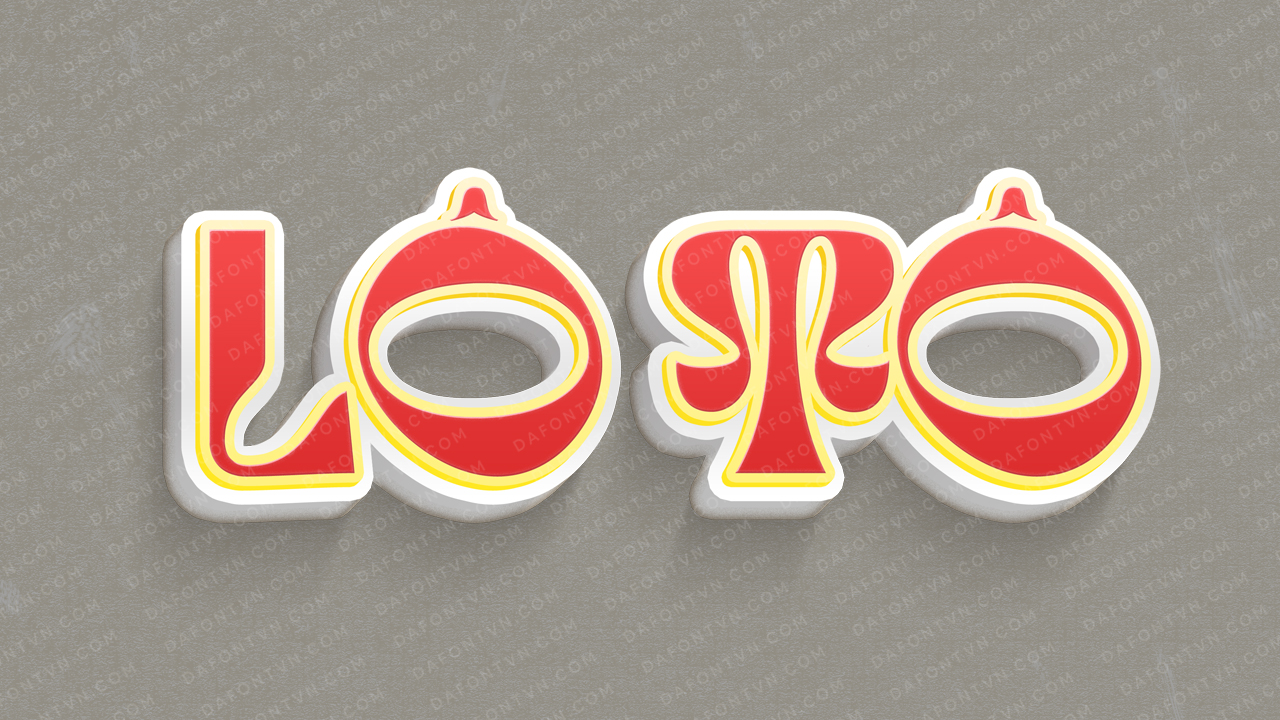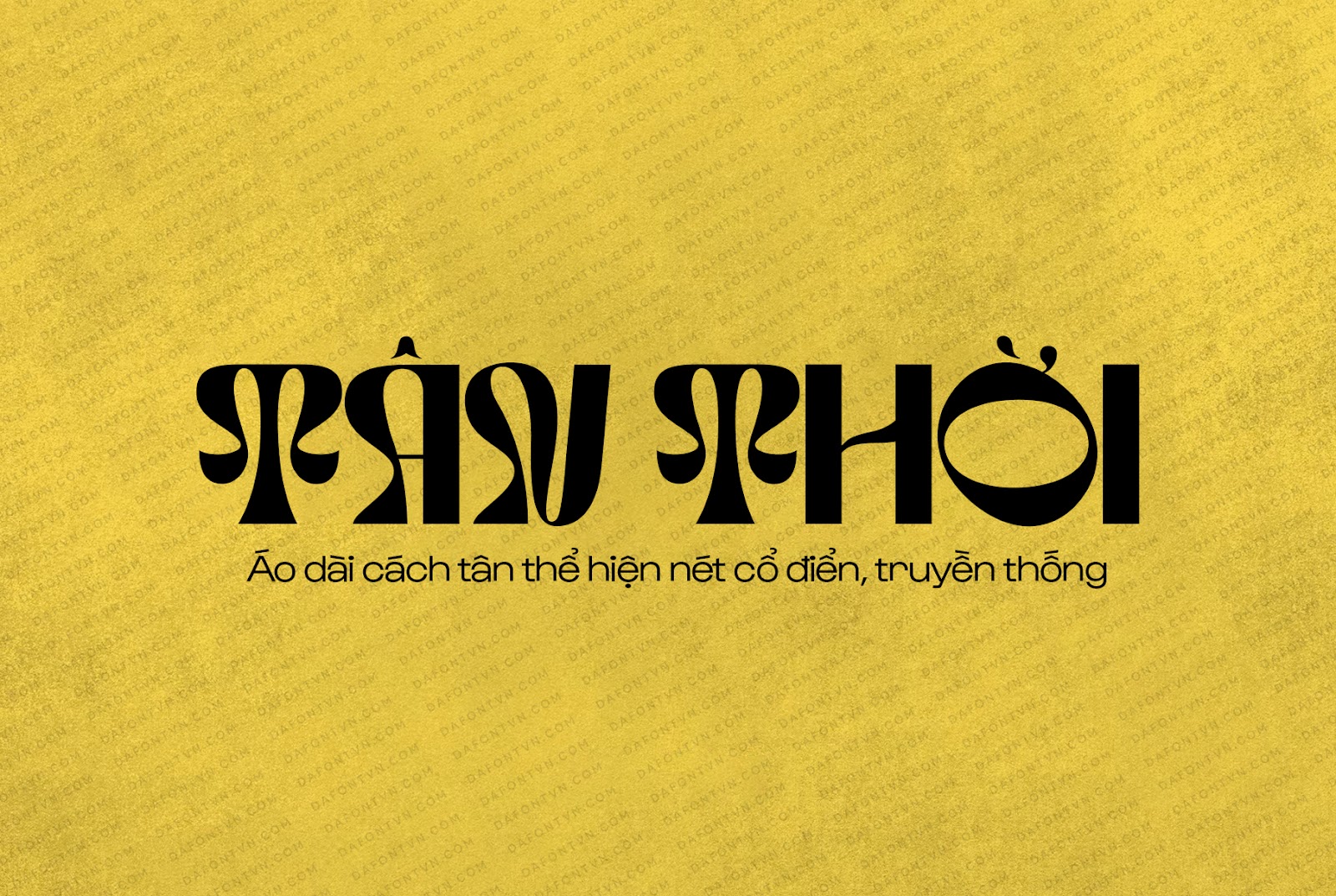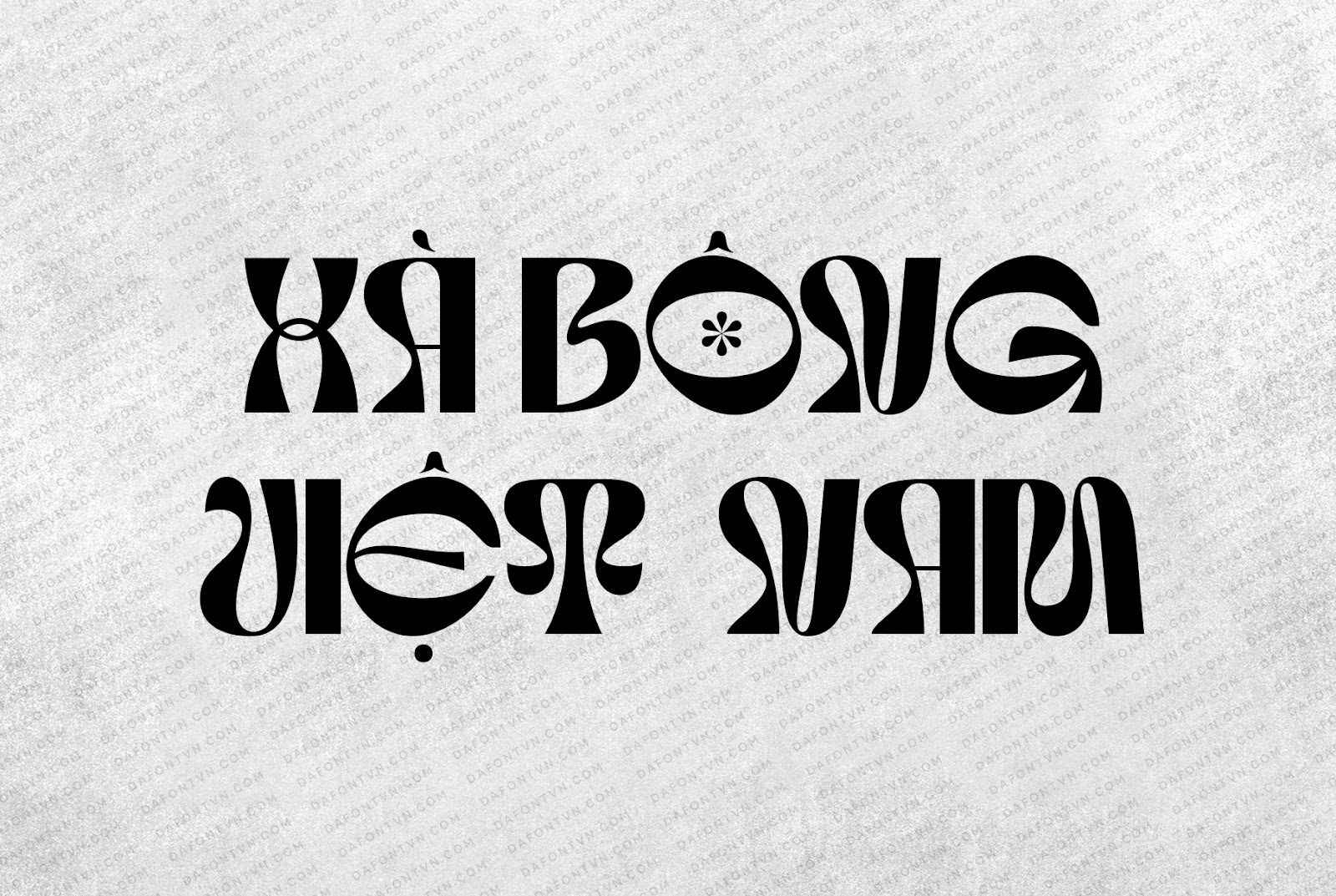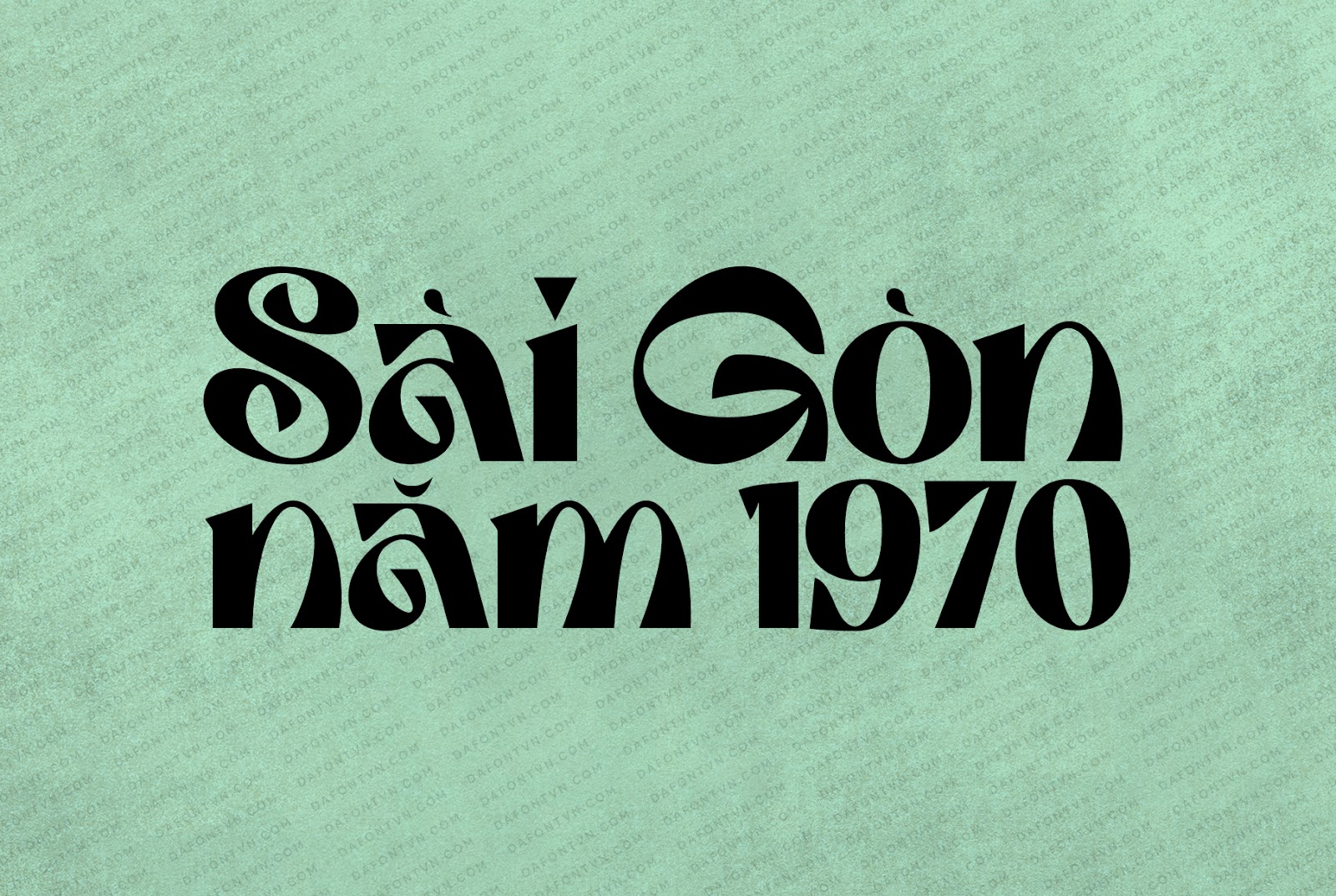
Font việt hóa Tango – Font chữ retro
Tango là một font chữ retro với các nét chữ đậm vì vậy mà nó phù hợp để sử dụng cho hiển thị. Phông chữ này hoàn hảo cho các thiết kế nhãn hiệu, bao bì sản phẩm, áp phích, logo, tiêu đề… Ngoài ra font chữ hỗ trợ tính năng OpenType bao gồm một số các chữ cái và chữ ghép thay thế.